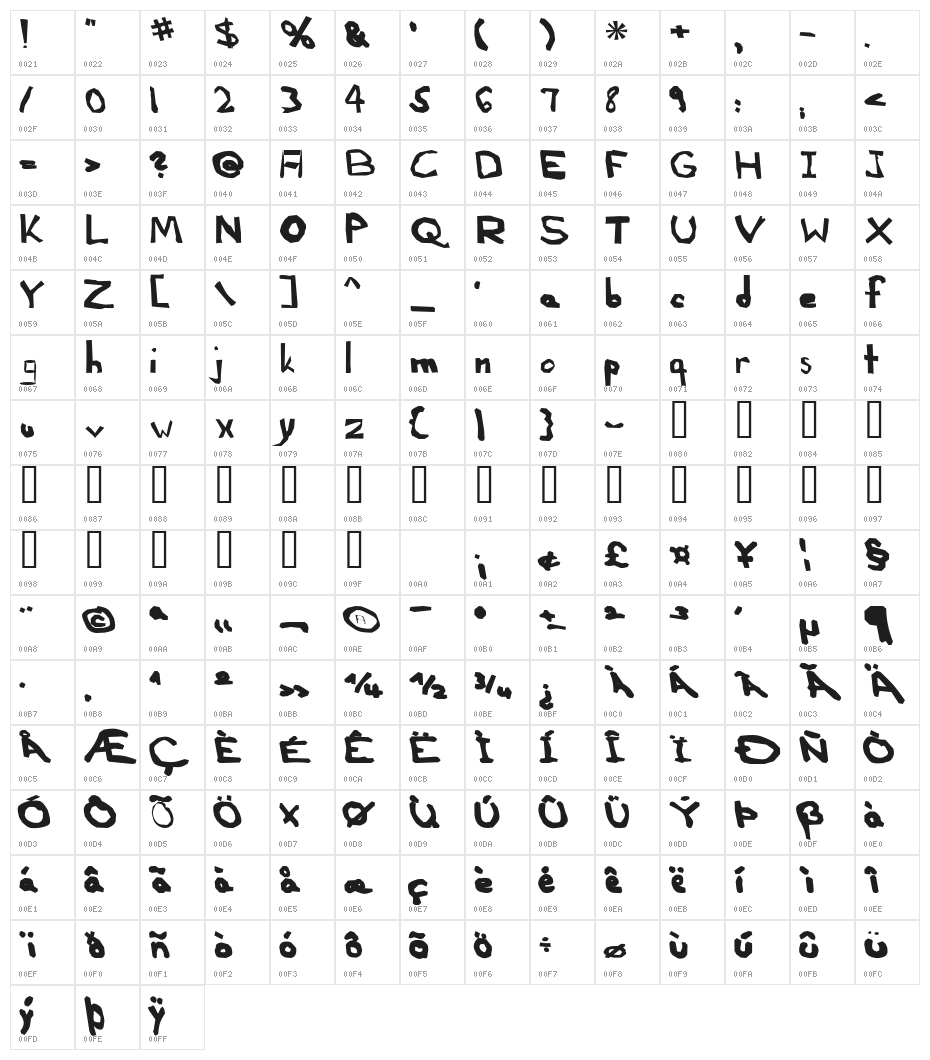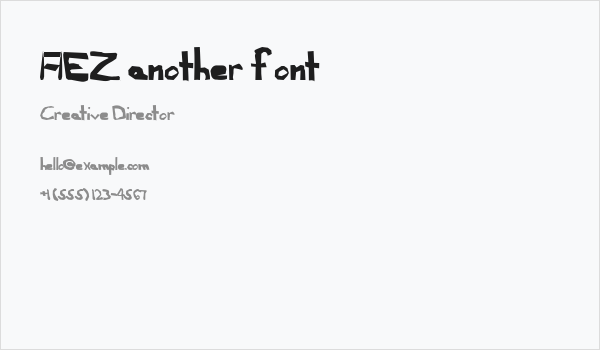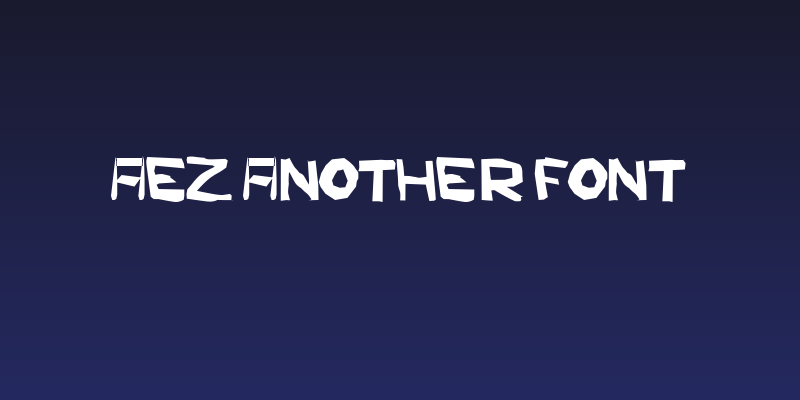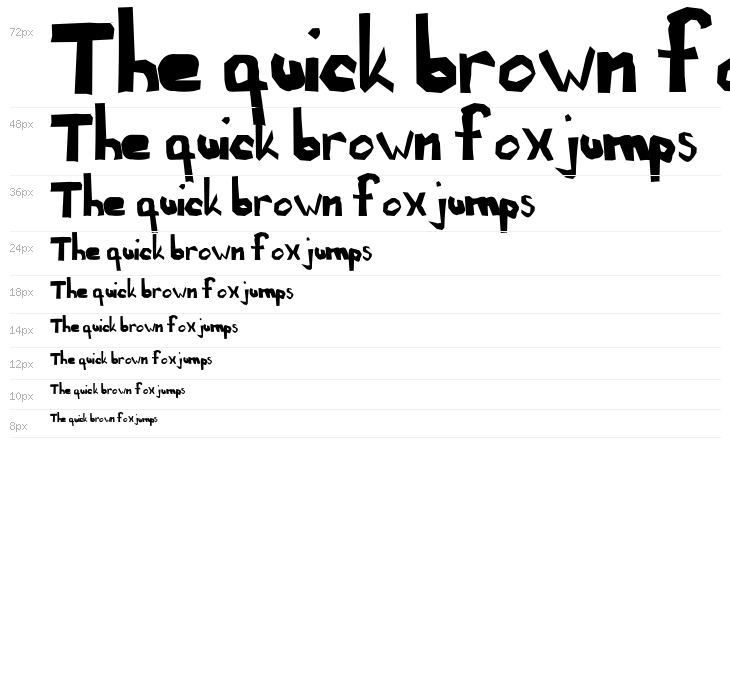
AEZ another font Font
✎ Messy
| Categorie | Messy |
| Stile generale | Modern, Edgy |
| Progetti proposti | Perfect for album covers, posters, graffiti art, and any project needing a bold, unconventional typeface. |